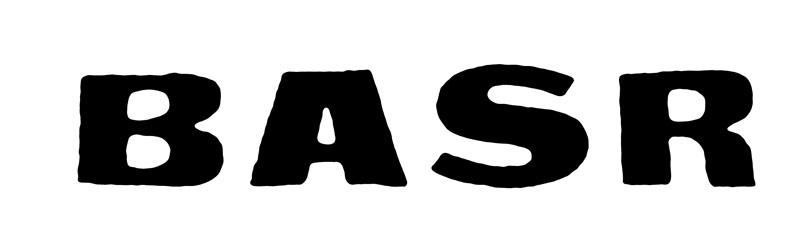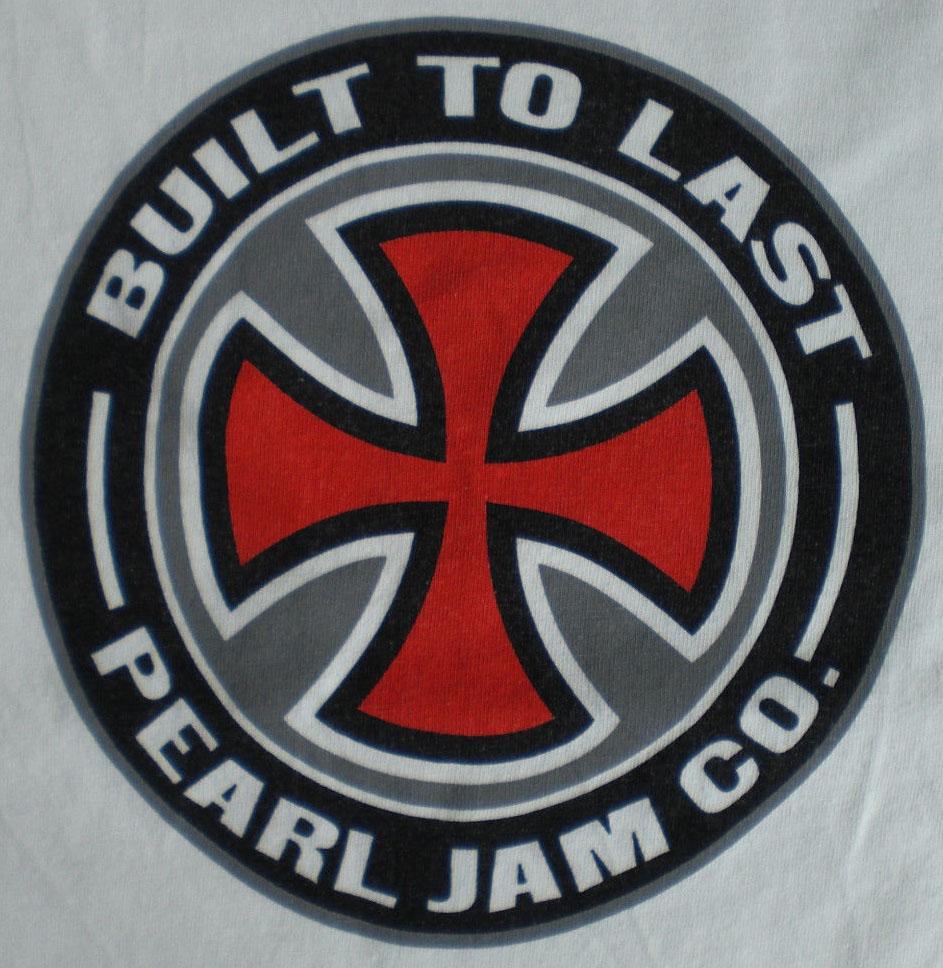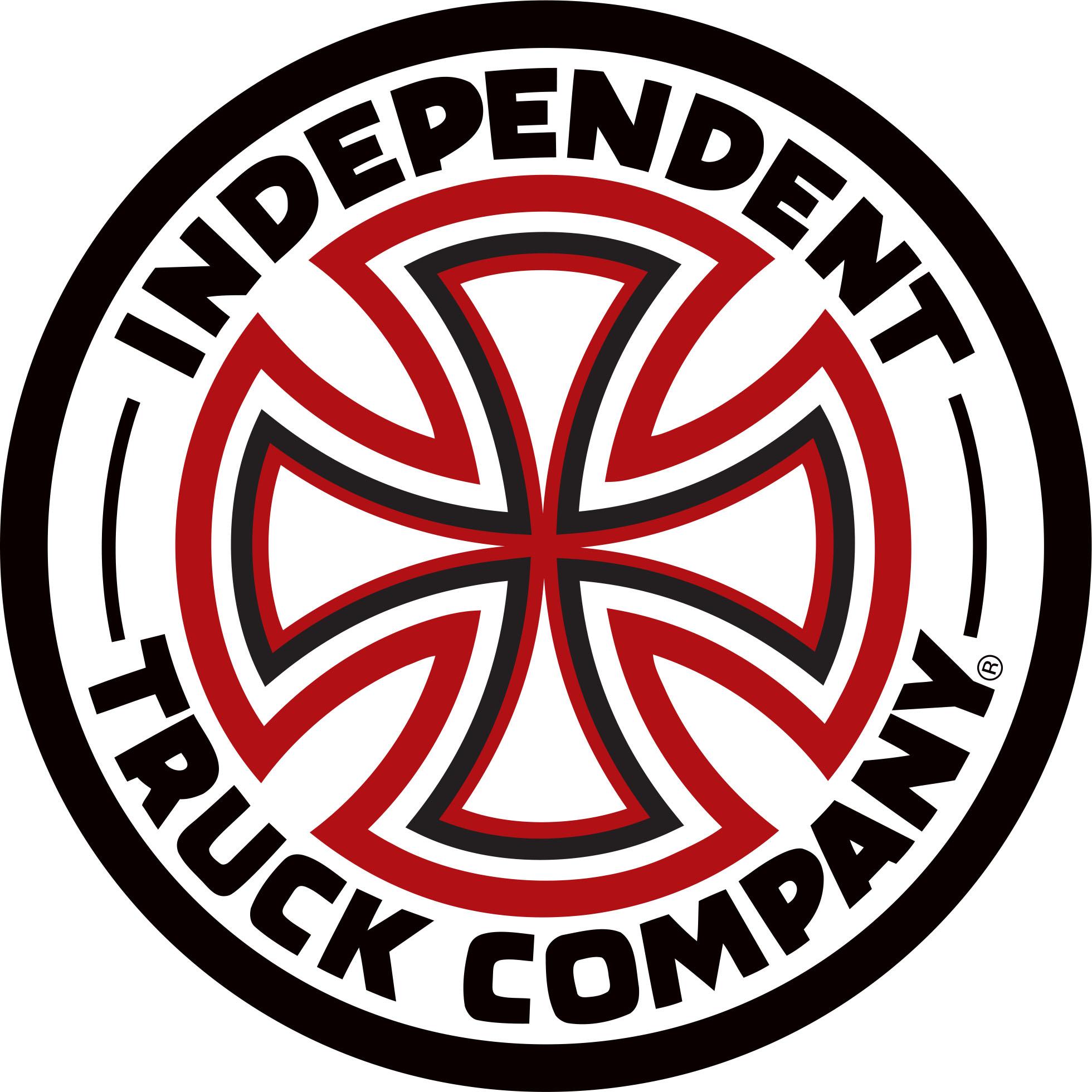
Schrift(en) aus Skateboardlogo/Pearl jam
ich bin auf der Suche nach zwei Schriften. Und zwar von der Marke „Independent“. Die Firma stellt Achsen für Skateboards her.
Das Motiv ist sehr beliebt, unter anderen hat die Band „Pearl Jam“  eine Adaptation des Logos rausgebracht.
Mich würden sowohl die Schrift aus dem original Logo (späte Siebziger), als auch die vom Pearl-Jam-Shirt (um 2010) interessieren.
Ja, schon klar. Nur welche Schrift liegt dem zugrunde?  Oder kennt eventuell jemand eine ähnliche?
Zum Kreuz steht hinter meinem Link (oben) übrigens: „Die Inspiration zum Logo des Alisee Kreuzes lieferte ein Bild des Papstes John Paul II, der das Symbol auf seinem Gewand in einer Ausgabe des Time Magazins trug.“
Nur welche Schrift liegt dem zugrunde?
Generell muss einer Beschriftung nicht unbedingt eine vorhandene Schrift zugrunde liegen. Das ist ja bei vielen Schriften aus meinem Sortiment auch nicht anders. Man hat eben eine Idee für einige besondere gestalterische Merkmale der geplanten Schrift, wie hier diesen speziellen Bogen im P, der dann überall wieder in Erscheinung tritt, wo ähnliche Formen in anderen Buchstaben erneut auftreten, also hier im R, oder vergrößert im D, und dann, hätte man daraus eine ganze Schrift gebaut wohl auch im B, ein anderes solches Element wäre das stark verrundete Rechteck beim O, das sich dann teils in C und U wiederfindet.
So kann praktisch jeder zum Schriftgestalter werden, und ich habe nicht selten spontane Beschriftungen gesehen, z.B. Demonstrationd-Transparente, die in soch einer spontanen Schriftgestaltung beschriftet waren.